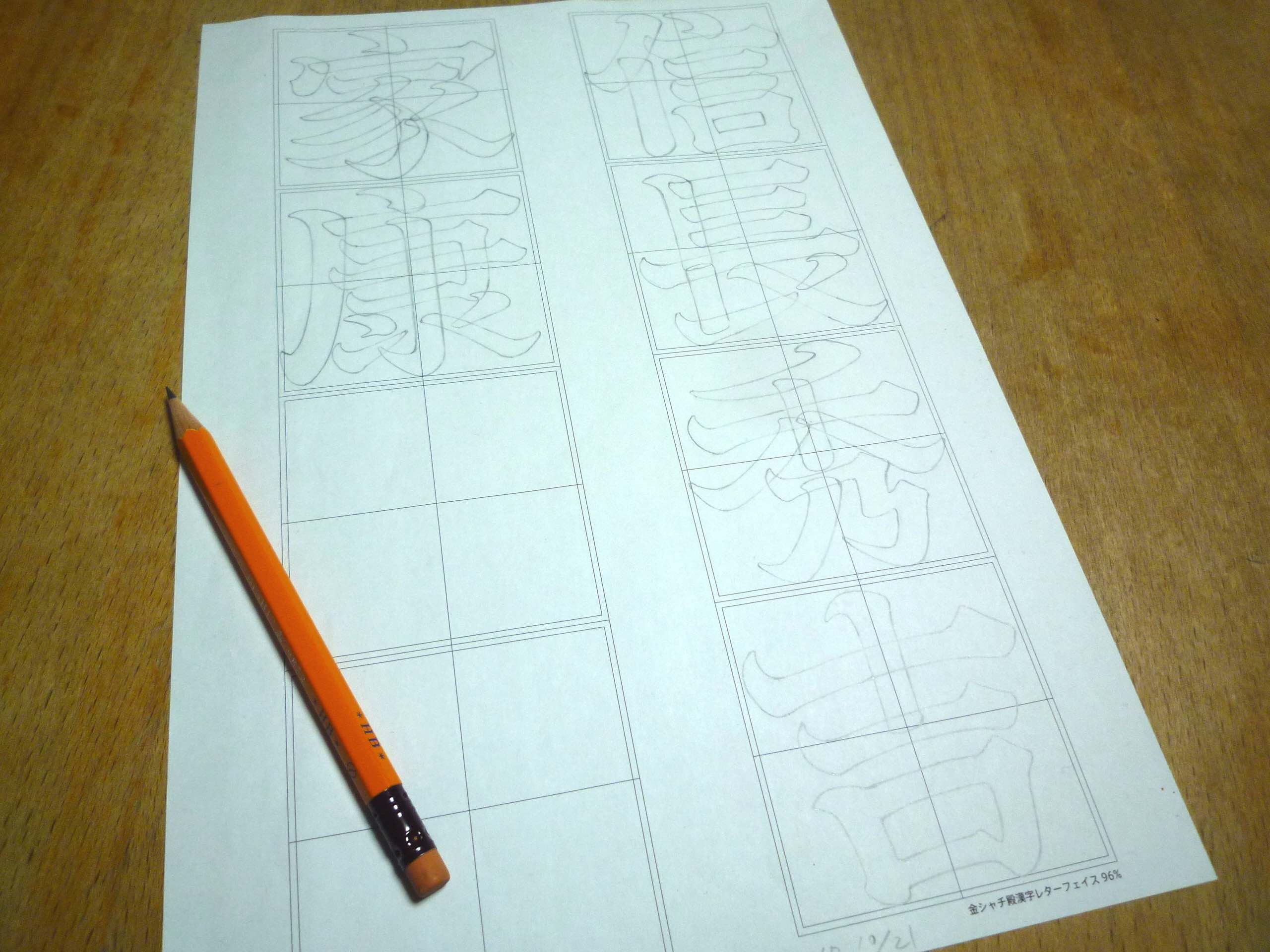
鳥よしでカレー風味のグラタンを食べたあと期日前投票へ。9割がたは高齢者の方々。台風が選挙結果にどう影響を与えるのかちょっと気がかり。金シャチフォント殿の漢字試作。
金シャチフォント殿かなの主要なカタカナがおおよそ出来たので、全体のバランスを見ながら調整をかけていく。ここからもう一段クオリティを上げれば、書体にいっそうの力強さが加わるはず。
オフィスのエアコン暖房を初稼働。漢字全文字のデザインチェックと10字ていどのブラッシュアップ。製品リリースのスケジュールと販売プランについて再度確認をおこなう。
次期リリースフォントの最終チェックと金シャチ殿かなの制作。インタビューには行かれず。昼は鶏の竜田揚げ定食。新米を大盛りで。